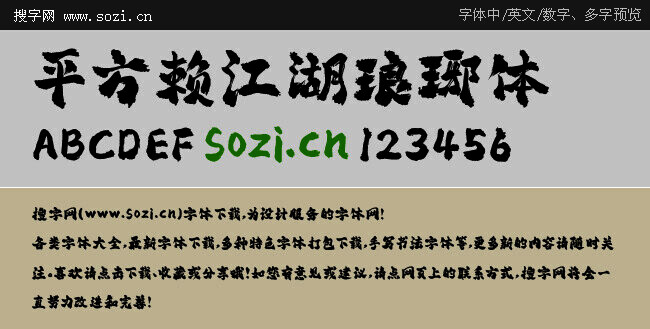
平方賴江湖瑯琊體
搜字網(wǎng)提供一款平方賴江湖瑯琊體中文書法字體下載,平方賴江湖瑯琊體是一款手寫風(fēng)格的書法字體,是一個(gè)具有毛筆飛白效果的書法藝術(shù)字體,字體線條粗獷厚重,筆畫遒勁有力,帶有古風(fēng)氣息,給人灑脫之感。適合包裝設(shè)計(jì)、海報(bào)設(shè)計(jì)、廣告設(shè)計(jì)等應(yīng)用。